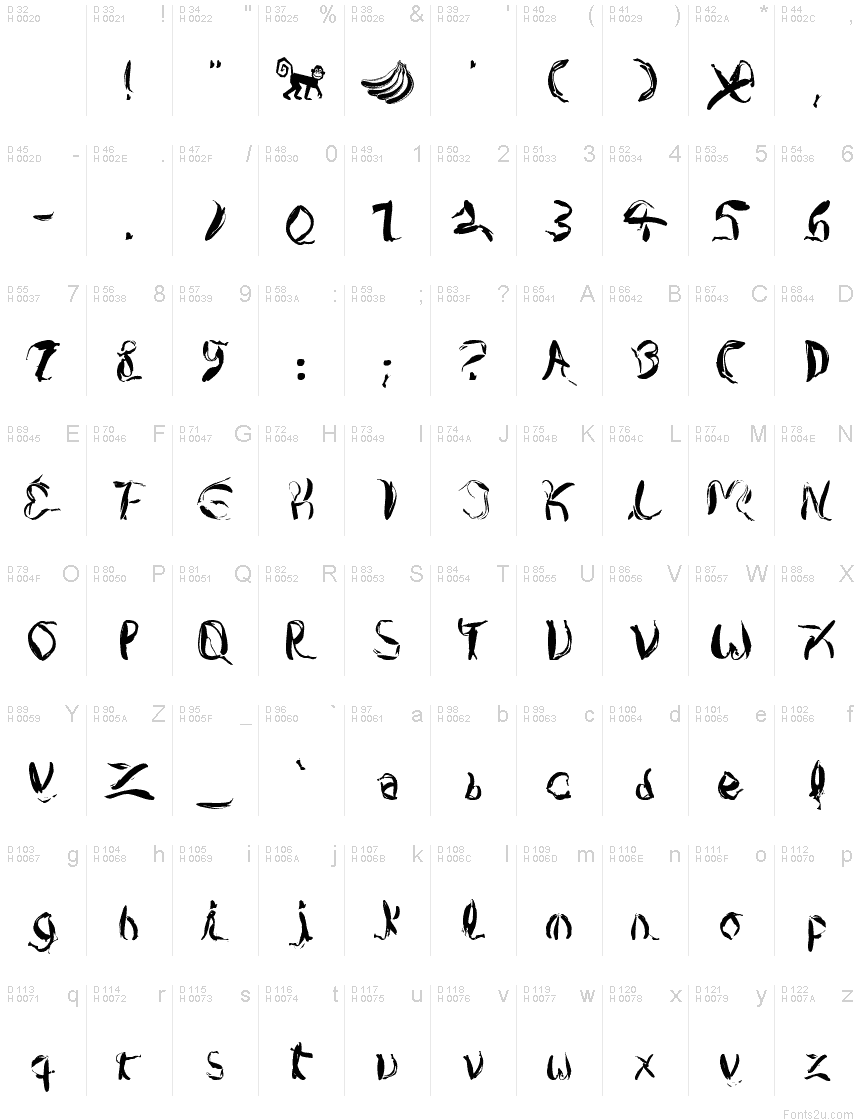
CopaBanana هو خط مجاني بنمط "جرونج" (grunge) يعتمد على ضربات الفرشاة، يبدو وكأنه خُط بقشور الموز المغموسة بالحبر. تلتوي الحروف وتتأرجح مع وجود ثغرات غير منتظمة في ضرباتها، مما يمنح كل كلمة طاقة مشوشة تبدو وكأنها باهتة بفعل الشمس. يتميز بطابع عفوي واستوائي ومجنون قليلاً، وهو رائع عندما تريد للنص أن يبدو كعمل فني أكثر من كونه مجرد خط طباعي.
باستخدام CopaBanana، يمكنك إضافة لمسة برية يدوية الصنع إلى ملصقات الحفلات الموسيقية، وتصاميم ركوب الأمواج أو التزلج، وقوائم مطاعم "تيكي"، والمجلات المطبوعة، ومنشورات المهرجانات، والشعارات الجريئة. يتألق هذا الخط المجاني عند استخدامه بأحجام كبيرة حيث تظل تفاصيله الممزقة واضحة؛ وللنصوص الفرعية الصغيرة، قم بإقرانه بخط "بلا زوائد" (sans serif) بسيط.